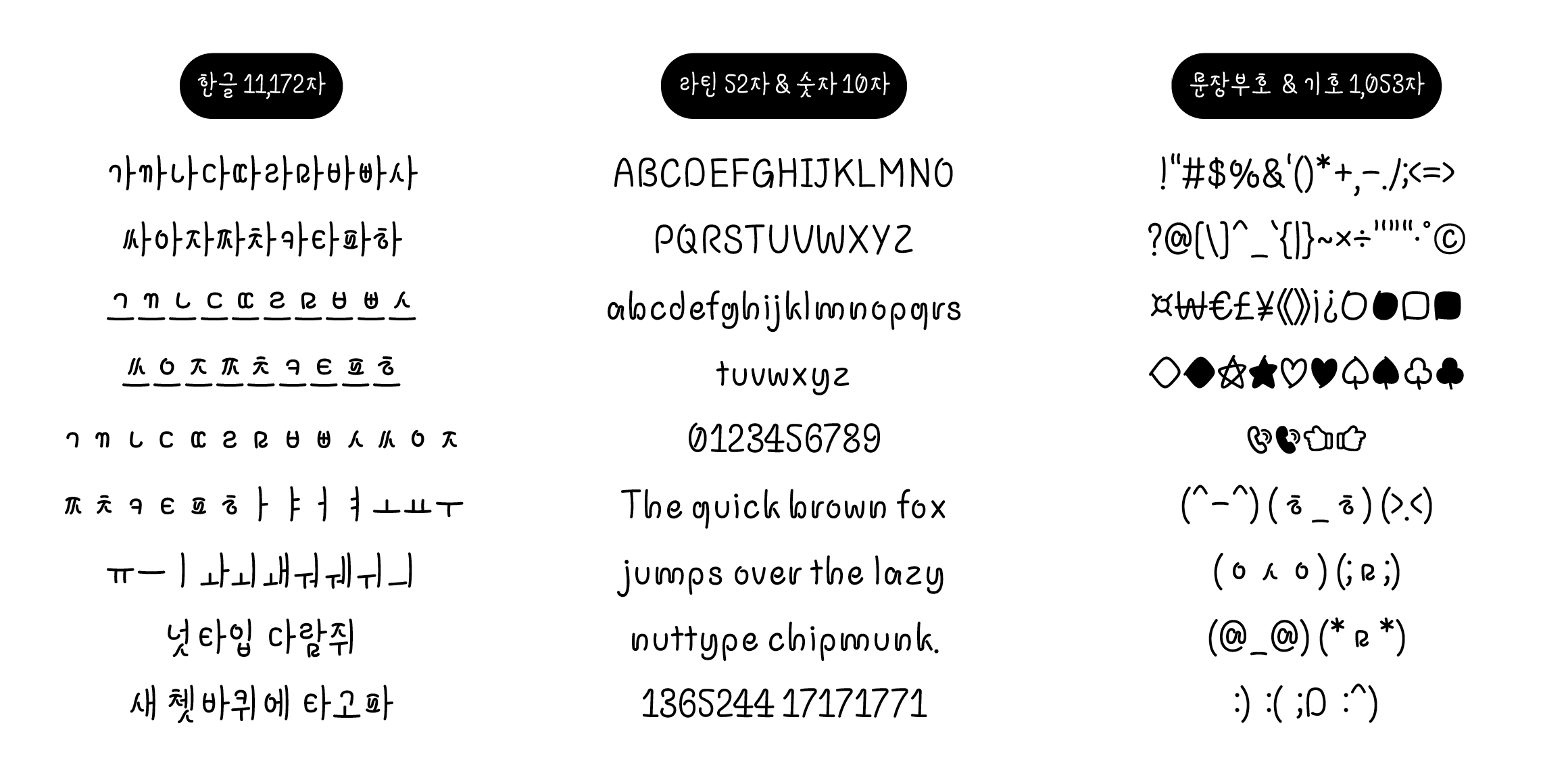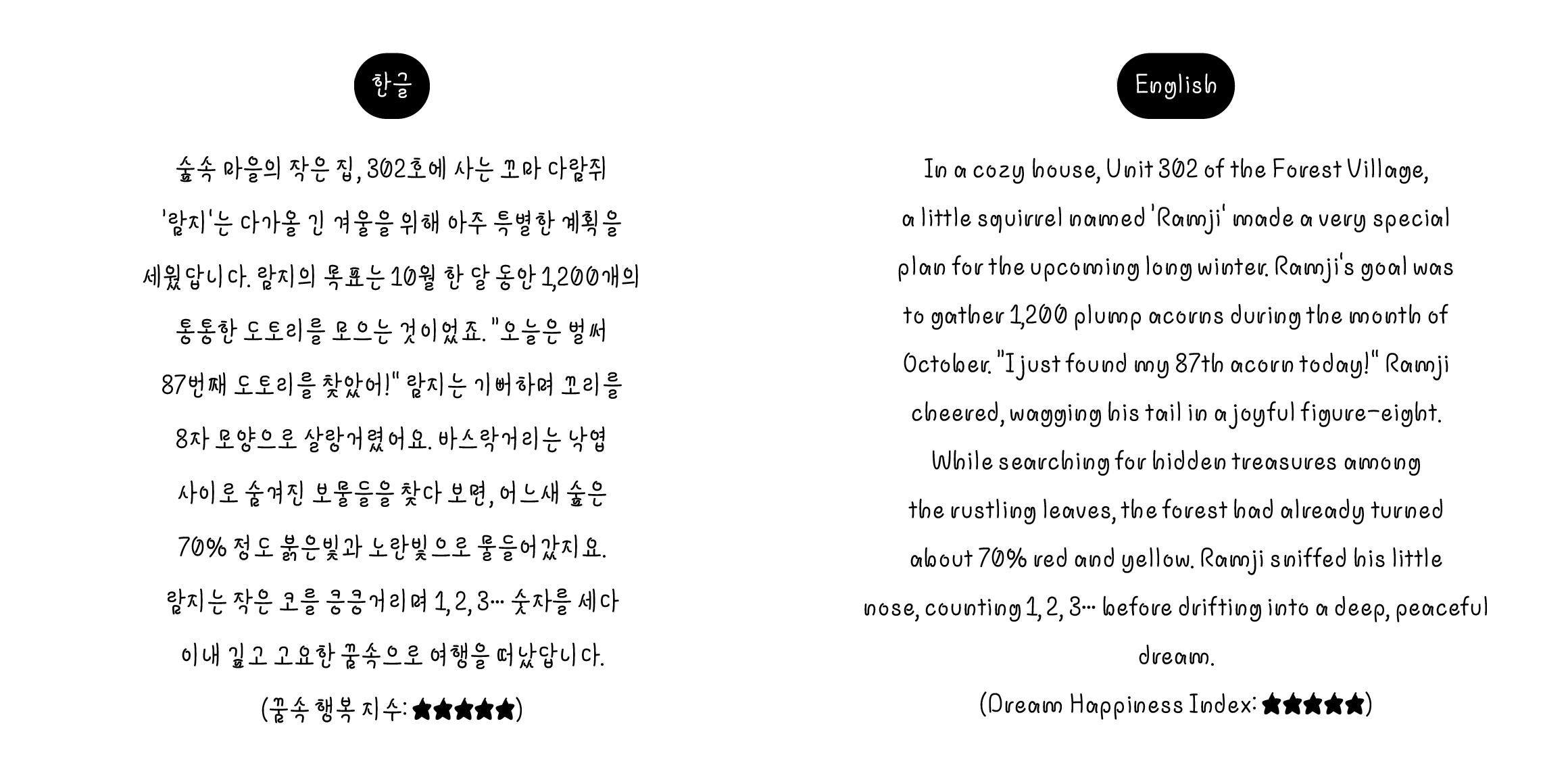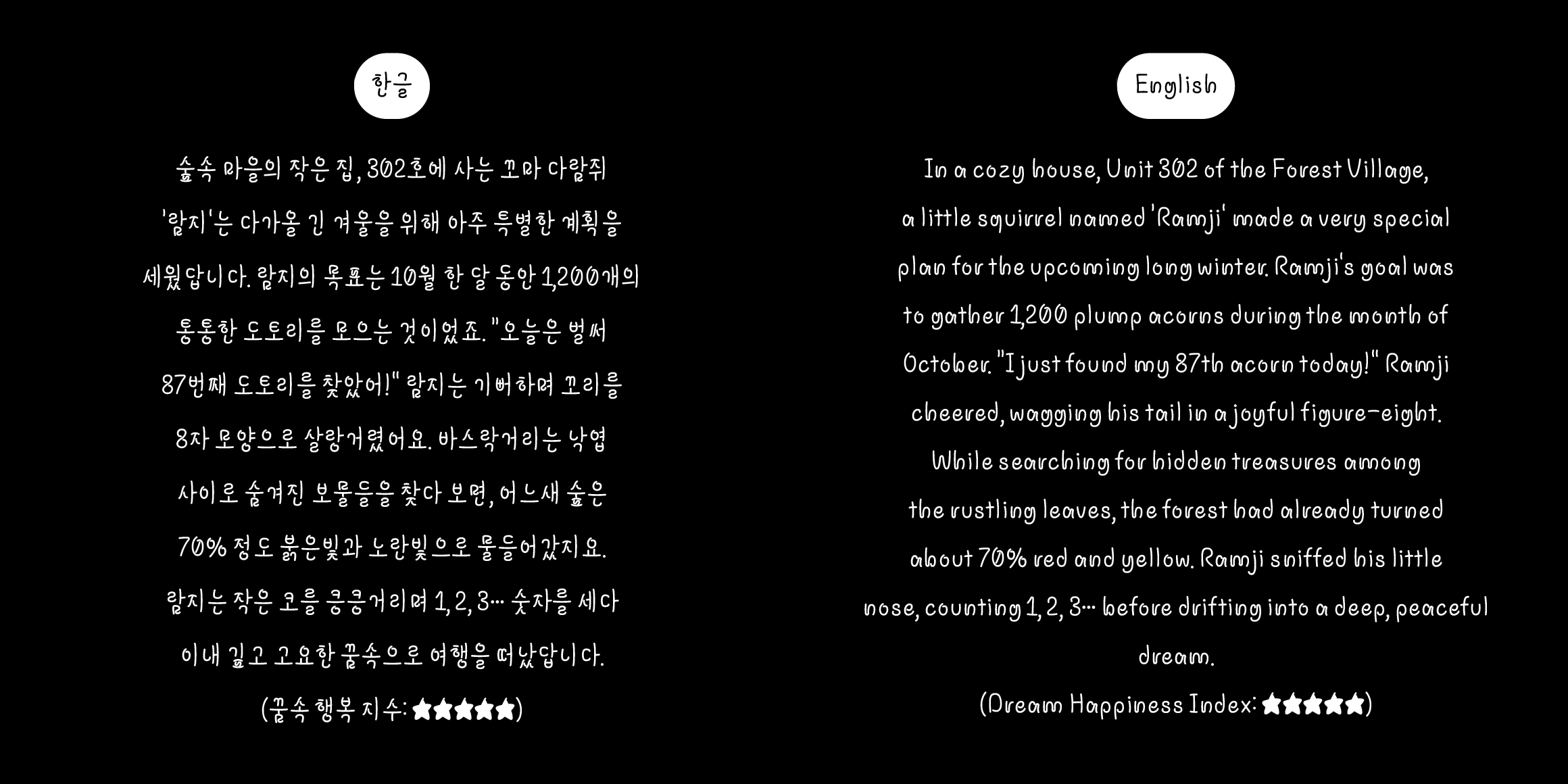
nut 식집사람지
Nuttype
분류 Script,손글씨
제목용영상개성적
물을 너무 줘도 문제, 안 줘도 문제. 햇빛이 너무 강해도 문제, 약해도 문제. 완벽한 조건을 갖췄다고 생각한 순간, 어느새 잎 하나가 노랗게 물들어 있다. 그럼에도 불구하고 식집사람지는 오늘도 화분 앞에 쪼그려 앉아 새 잎이 돋아나길 기다린다. 그리고 식물이 새 잎을 내밀기라도 하는 날엔, 그 작은 연두빛 앞에서 한참을 멍하니 서 있다가 혼자 조용히 눈물을 훔친다.
• 한글 11,172자 / 라틴 52자 / 부호 1,053자 / 숫자 10자
• Script,손글씨
• nut 식집사람지 / nut Plant Parents Ramji